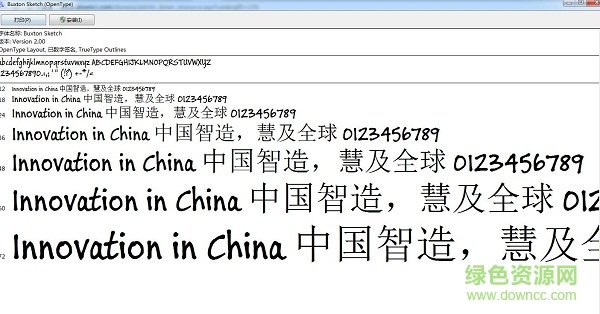
buxton sketch字體是一款漂亮的手寫英文字體,筆畫生動(dòng)自然,結(jié)構(gòu)完整,造型比較隨意,可以用于信書設(shè)計(jì)、平面設(shè)計(jì)、賀卡等方面,歡迎大家免費(fèi)下載!
很多人認(rèn)為在設(shè)計(jì)上,手寫體的使用是與眾不同的明智之選。因?yàn)槭謱戵w不僅僅有創(chuàng)造性,甚至有些看上去像真的手寫的一樣,這樣的設(shè)計(jì)更能吸引用戶的眼球,引人注目。